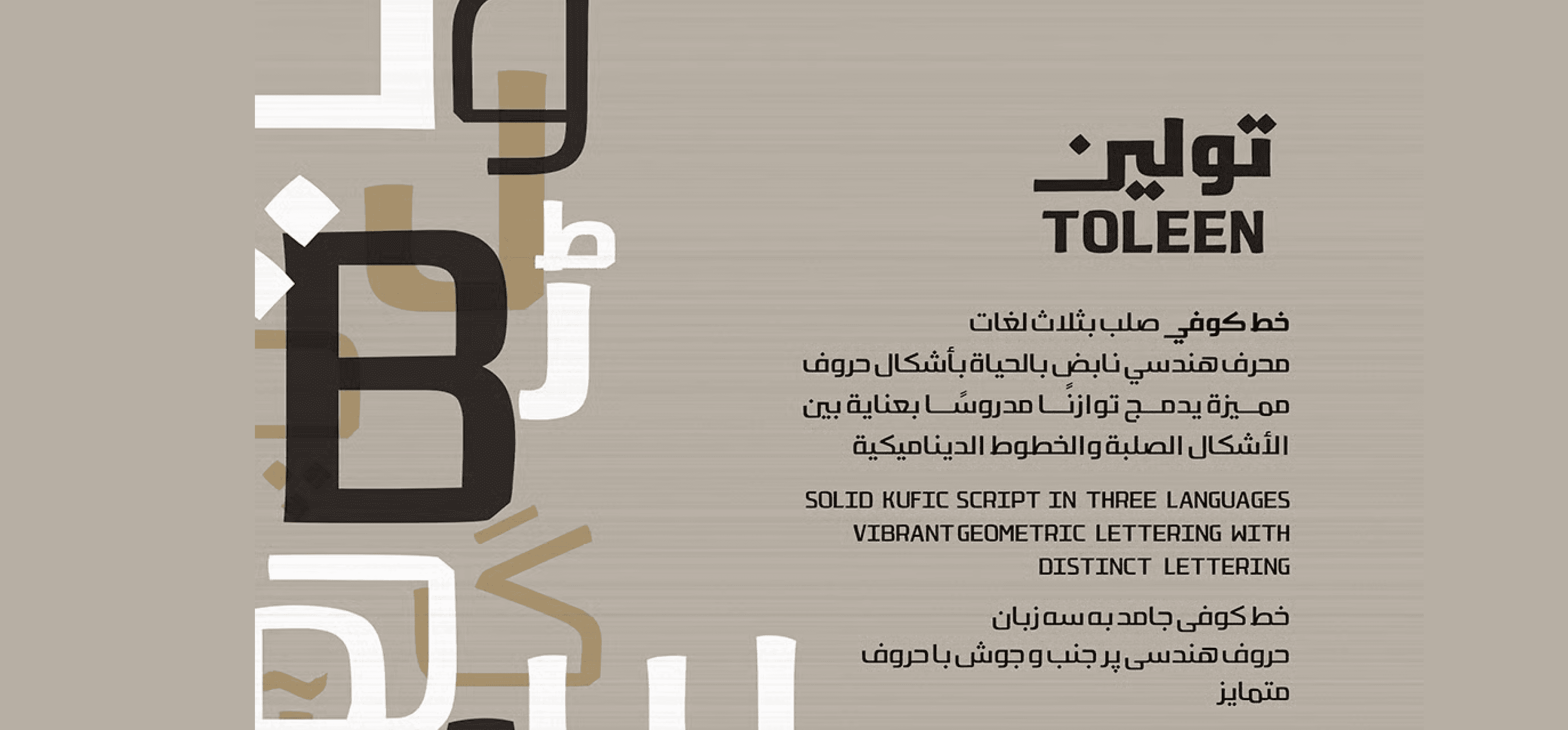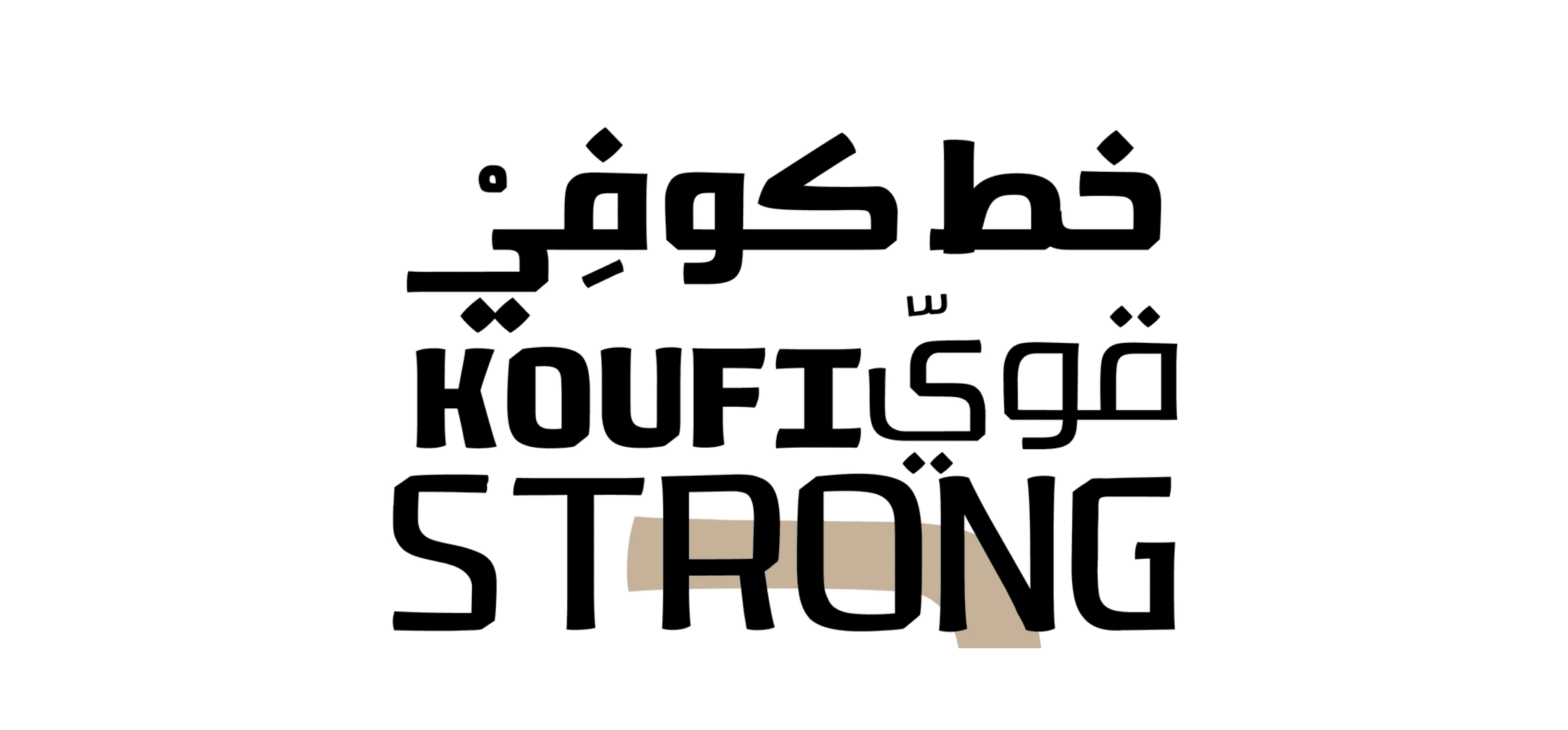
تولين – TOLEEN
خط كوفي صلب بثلاث لغات
محرف هندسي نابض بالحياة بأشكال حروف مميزة يدمج توازنًا مدروسًا بعناية بين الأشكال الصلبة والخطوط الديناميكية.
SOLID KUFIC SCRIPT IN THREE LANGUAGES
VIBRANT GEOMETRIC LETTERING WITH DISTINCT LETTERING
خط كوفي جامد بثلاث زبان
حروف هندسي پر جنب و جوش با حروف متميز